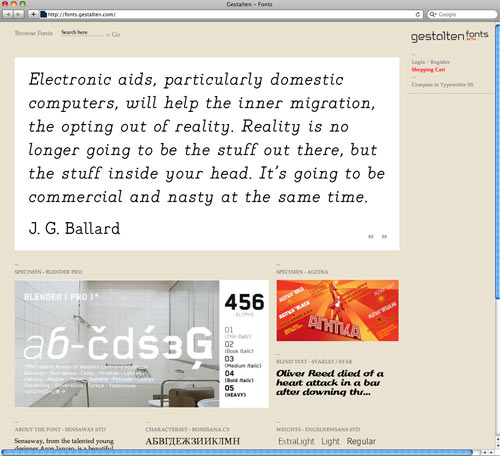
Neu: Gestalten Fonts Webseite
Seit heute werden Schriften von den Gestalten auf einer eigenen Webseite präsentiert. 2003 wurden das erste Mal zeitgenössische Schriften neben Büchern im Sortiment angeboten, heute vertreibt Gestalten schon ca. 120 Schriften. Herzlichen Glückwunsch zu diesem Schritt!
Since 2003, Gestalten has continued to offer a versatile selection of cutting-edge fonts created by designers and typographers for designers. Gestalten Fonts offers a roster of over 120 contemporary typefaces through our indepenent font foundry.
Diverse in style from refined, elegant, and minimal text fonts perfectly suited for editorial designs to more experimental display, ornamental, script, blackletter, monospaced, stencil and typewriter fonts, all have been handpicked by our esteemed graphic designers and editors.
Gestalten specializes in developing content for aficionados of cutting-edge visual culture worldwide. The company is best known for the more than three hundred and fifty books we have published that document and anticipate vital design movements.
Keeping with the Gestalten philosophy, firmly committed to presenting design excellence in cutting-edge visual culture, Gestalten Fonts delivers an inspiring collection of typefaces to enrich and distinguish your visual language.